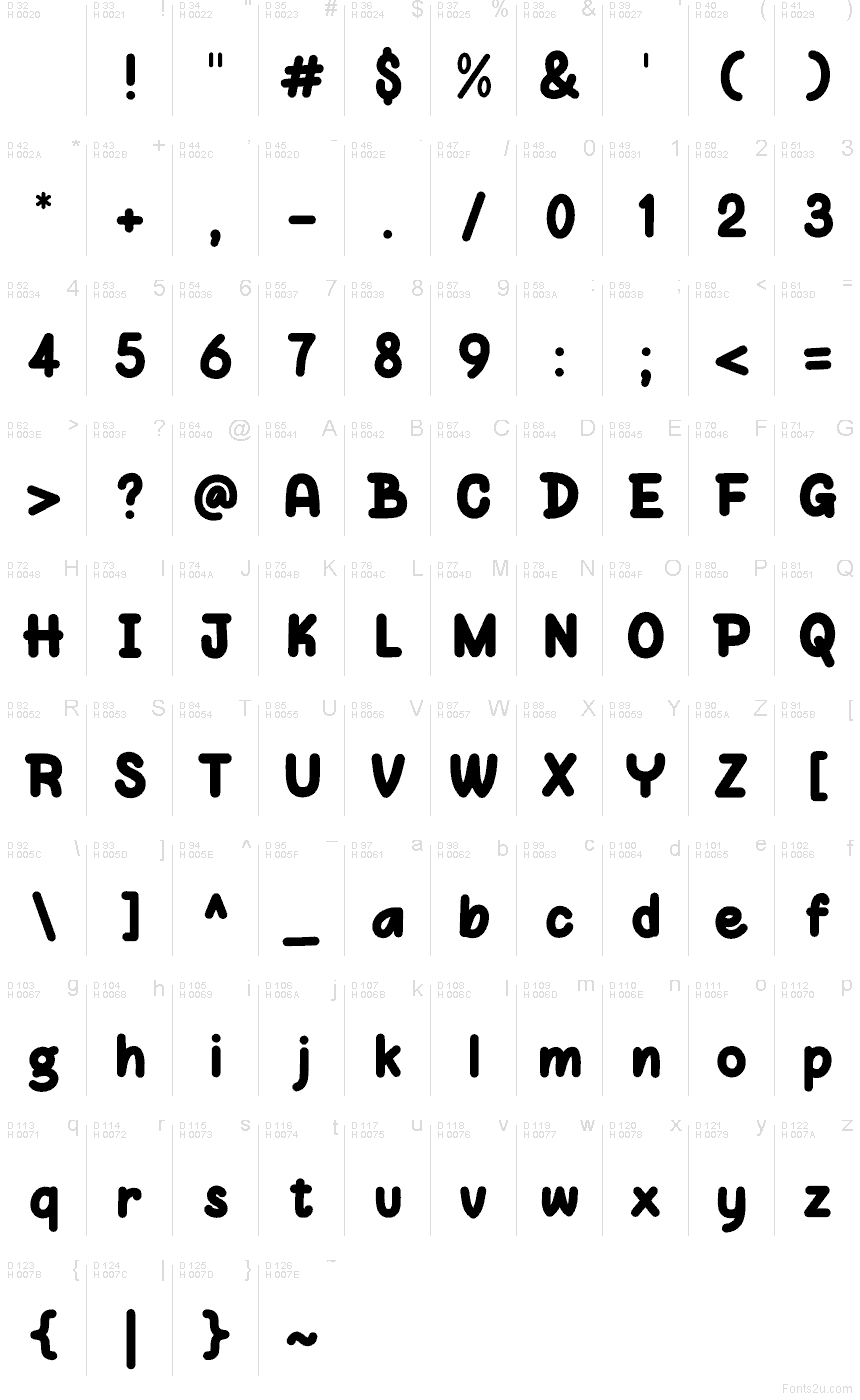
Awal Mondok
Awal Mondok від Hello Good Studio - це безкоштовний коміксний шрифт з округлими «бульбашковими» формами літер та м'якими краями. Накреслення виглядає розслабленим, наче його малювали від руки, а плавний ритм надає шрифту дружнього та неформального тону, не створюючи відчуття хаосу.
Awal Mondok чудово підходить для дитячих проектів, заголовків на плакатах, логотипів, пакування, графіки для соціальних мереж та коротких анонсів подій. Цей безкоштовний шрифт додає невимушеного, мультяшного характеру дизайнам, яким потрібно трохи чарівності та легка, проста візуальна присутність.